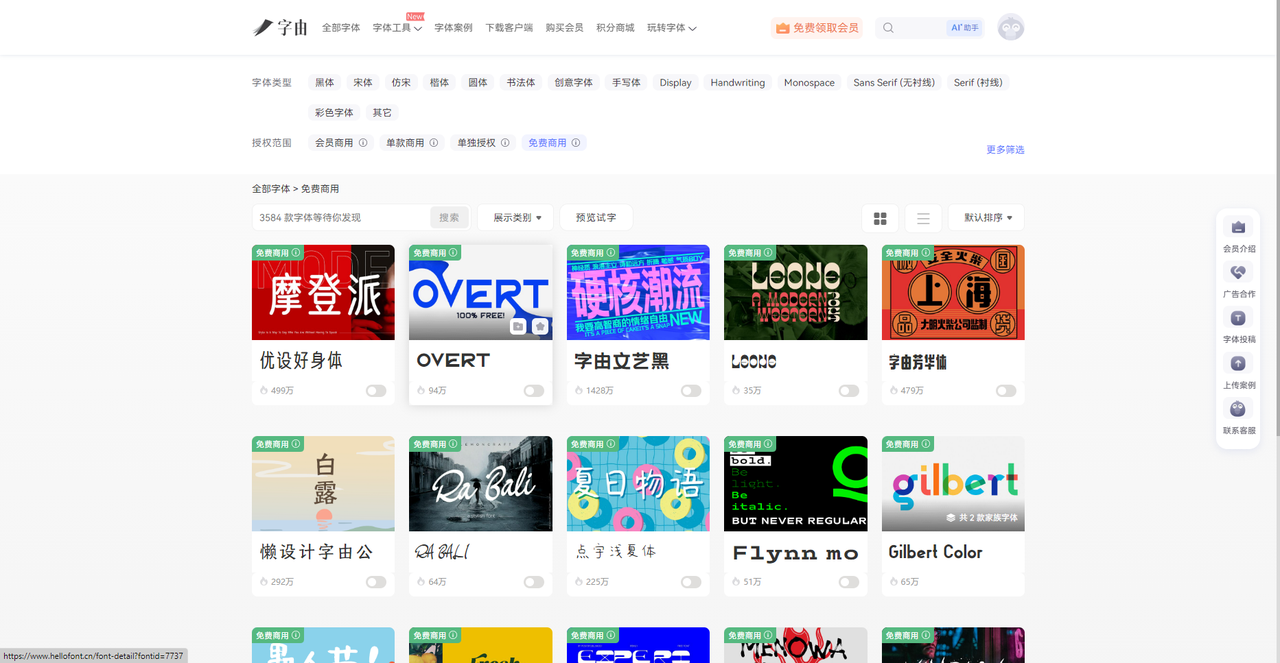
PS字体库下载免费网站有哪些?推荐这6个
打断创作节奏的往往不是使用 PS 时的卡顿,而是换字体。本来用的这款字体觉得还不错但是当设计进一步调整的时候发现现在用的字体又有些违和感,这时候要换字体的话还需要切出软件去各种网站上搜索、下载、安装、替换字体,并且还需要重启 PS 才能看到效果。不过这么一折腾,灵感估计就偷偷溜走了。但是我想说的是,市面上其实有现成的很多 PS 字体库,打包好的字体能够直接使用,不用再大费周章了。今天我就给大家整理了 6 款亲测好用的 PS 字体库下载网站,希望能够帮到你们!
第一个要推荐的 PS 字体库是字由。它最大的亮点是直接把 5000 多款字体打包成一个“字体库”——你不需要一个一个下载、安装,打开客户端就能用。接下来我将为大家详细介绍。
如何用字由找到自己想要的字体
- 打开以后就可以看到主页左上角有“全部字体”的选项,点进去以后就可以看到如下界面,左侧是详细的筛选栏:
按类型:黑体、宋体、书法体、手写体、Sans Serif、Serif等
按热度:每款字体右下角有使用次数,优先选热度高的
- 如果你想预览一下字体效果,可以直接点击自己感兴趣的字体,就会自动跳转到预览界面,实时看效果。不用下载就能知道这款字体适不适合。
一键应用到 PS
在PS里选中文字图层,回到字由客户端点击想要的字体,PS里的文字实时切换。整个过程不需要下载、安装、重启,试一款字体只要1秒钟。
推荐几款我常用的字体
- 优设好身体(499万次使用):优设团队出品,字形方正饱满,适合正文排版和简洁标题。做画册、公众号配文很好用。
- 字由芳华体(479万次使用):手写风格,笔画柔和,适合文艺类设计,比如诗集封面、明信片。
- OVERT(94万次使用):现代无衬线字体,线条干净,适合网页设计、UI界面。
- 点字浅夏体(225万次使用):清新手写体,适合夏日主题、少女风格的设计。
最主要的是字由还支持上传本地字体到云端,在A电脑上传,B电脑登录账号直接激活使用,不用U盘、不用网盘。电脑坏了也不用担心字体丢失,只要账号在,字体就在。
2、Freepik
Freepik 是全球知名的设计资源平台,很多人用它找矢量图、PSD模板,其实它的字体网站免费下载版块也很丰富。我喜欢用这个网站最主要的原因就是这个网站里有很好的实时预览字体效果框,可以输入文字、调整字号,很直接地就能看到效果,展示的示例字体有 Mirth、Wiggle Puff、Tidal Roll、Brass Ghost 等,风格现代,设计感在线。并且需要付费还是免费都说得很清楚,免费字体通常标注“Free for personal use”或“Free for commercial use”,下载前可以查看具体授权。
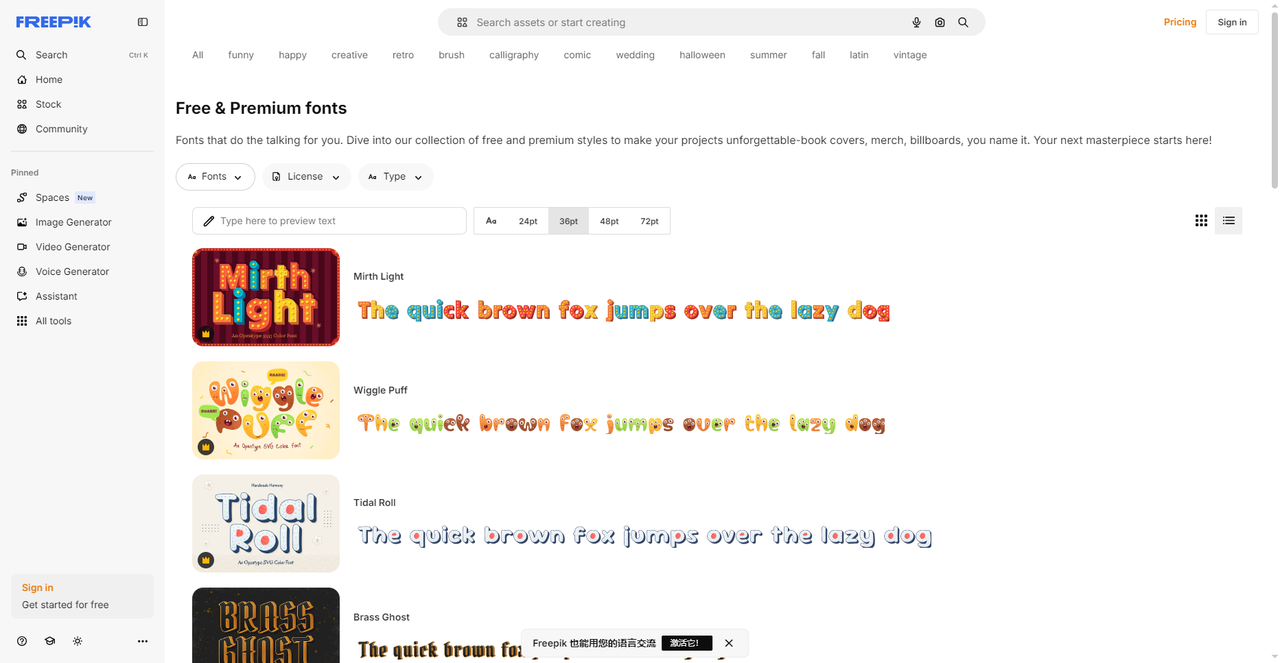
3、Free Photoshop Fonts
Free Photoshop Fonts 是 FixThePhoto 团队整理的ps字体库,专门针对摄影后期设计。网站上的字体都由专业修图师挑选,适合加在照片上作为水印、标题或装饰文字。每款字体都标注了“Free Font”,直接下载安装即可。如果你做摄影后期、需要给照片加文字,这个ps字体库很对口。
4、1001 Free Fonts
1001 Free Fonts 是一个老牌ps字体库,收录了超过10000款免费字体。网站首页按字母A-Z排列,也有详细分类:3D、Brush、Decorative、Fantasy、Handwriting、Modern、Rounded、Square等。这个网站的特色包括一键下载(需要注意版权问题)、分类细致(主页可以看到有很多标签,能快速定位到特定风格)、预览方便(可以输入文字,调整大小颜色,直接看到文字效果)。网站还提供“Buy Commercial License”选项,免费字体主要用于个人项目,商用需购买授权或仔细核对。
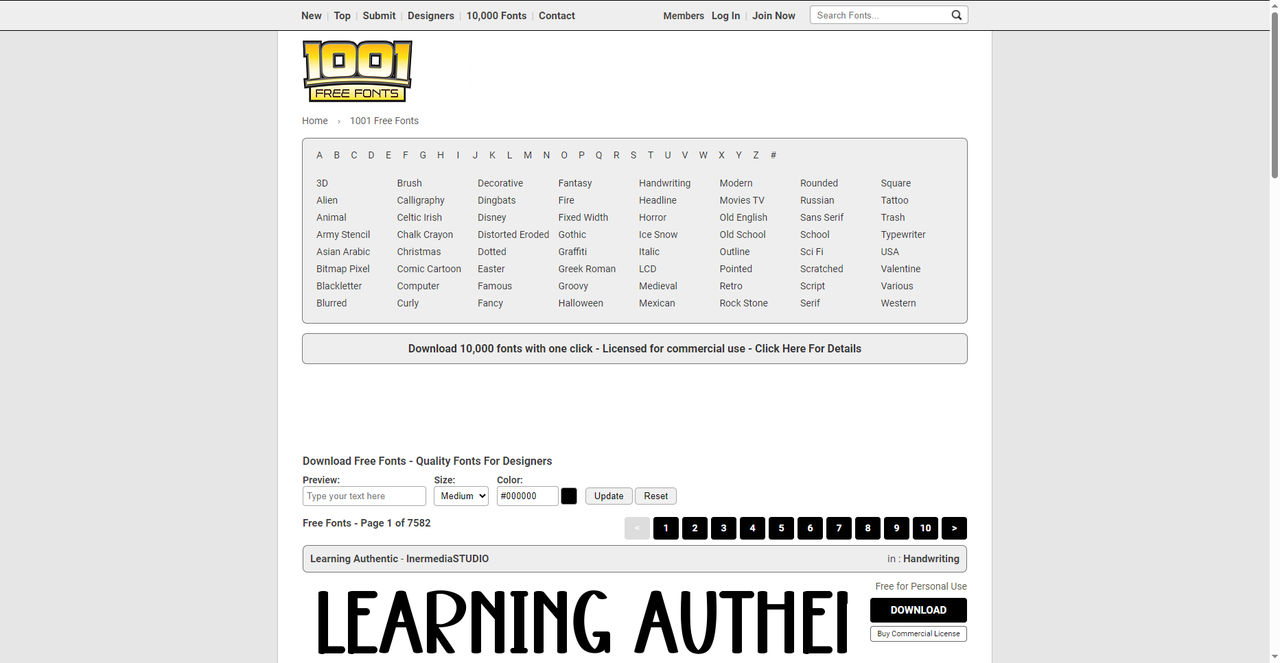
5、PS Fonts(Fontega)
这个区别于传统的字体网站,它准确来说是是设计师社区分享的ps字体库资源。比如 akowens89 发布的“DOWNLOAD 10 FONTS”包含10款精选字体,有 The Rave Is In Your Pants(Chequered Ink)、Emotion Engine(Pixel Sagas)等。我感觉社区推荐的话要比自己找更加方便,毕竟这些都是设计师师门自己亲自使用过后推荐的字体,次分享几款到几十款,适合想淘小众字体的设计师。设计师们分享的字体大部分免费,但商用需查看具体授权。
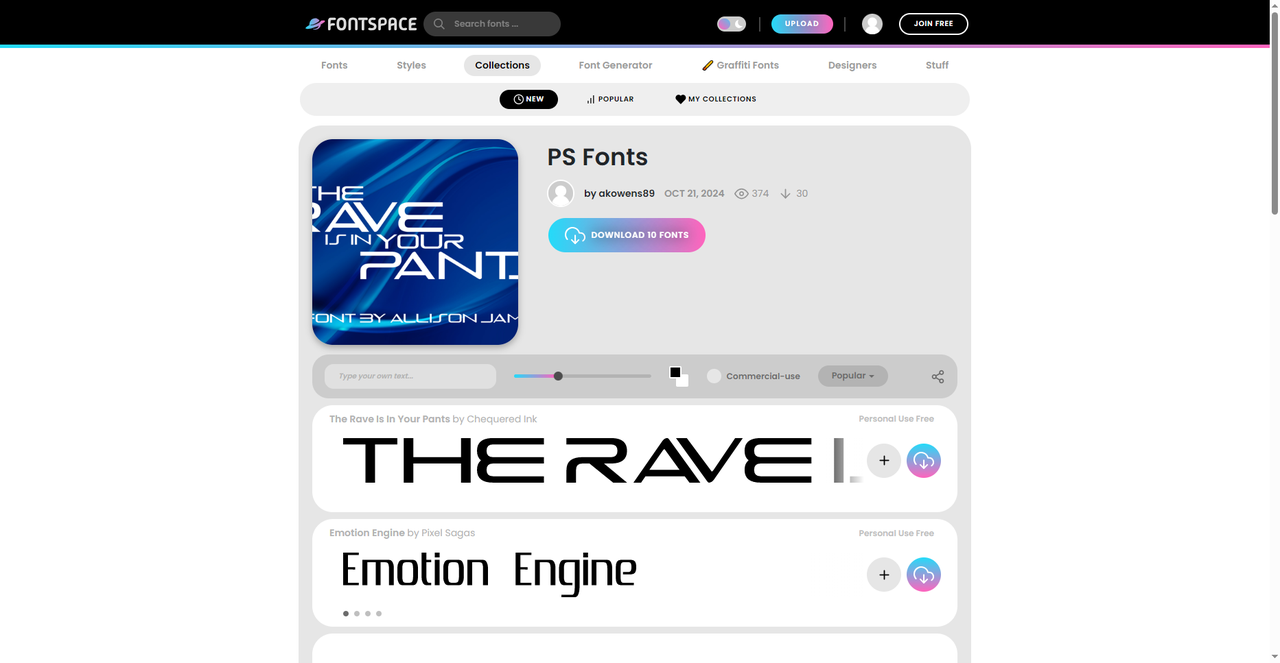
6、Fonts(Abstract Fonts)
Fonts(Abstract Fonts)是一个分类简洁的ps字体库网站。首页分三大类:Serif、Sans Serif、Script,每款字体都有预览图和字符数标注。
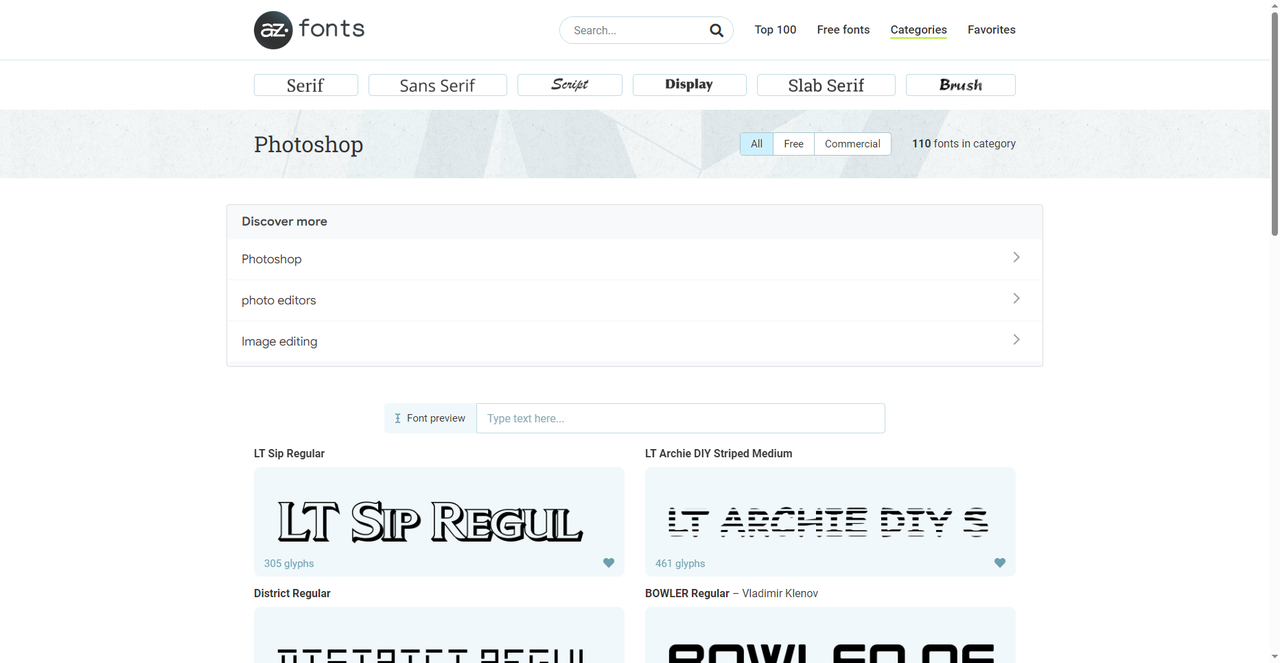
这 6 个ps字体库下载网站基本上涵盖了我设计工作上的所有需求,比如说Free Photoshop Fonts 专注摄影后期,1001 Free Fonts 数量够多、分类细致,社区分享的字体能淘到小众款,Abstract Fonts 分类简洁明了。但是我用的最多的还是字由,除了他是一个巨大的字体库以外,PS 上的一键换字体特别省事,而且个人云字库会随着我的账号更新而保存,设计过程中会省心省力。如果需要的话我把字由官网链接放在这里,需要的自取!